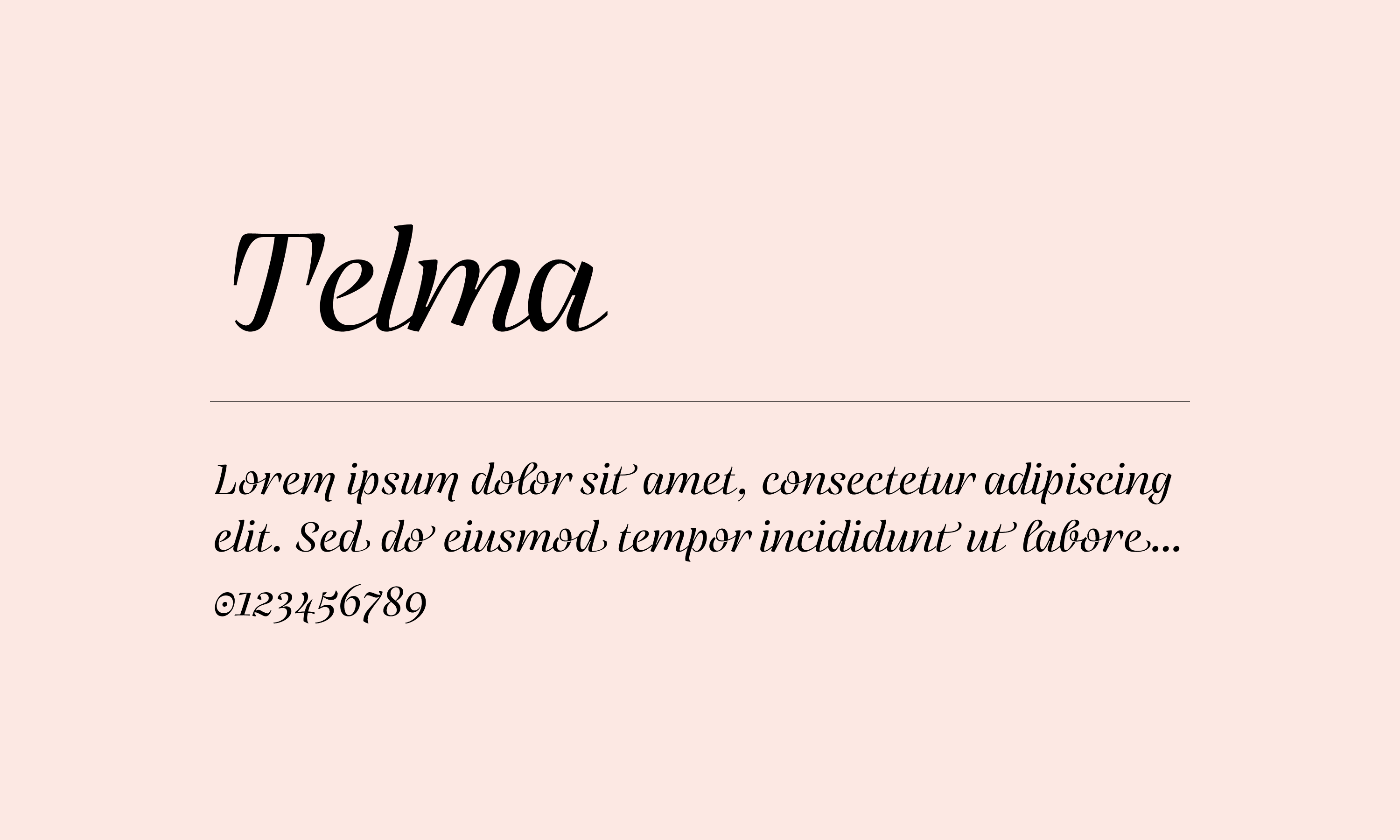
Telma
Telma 是一款非正式手写体字体家族。它的字形具有明显的粗细对比,这种对比赋予了某些字符的古怪结构一种更正式的特点。Telma 字体家族有五种字重,从 Light 到 Black 不等。每当字重增加时,字体的粗线条变得更粗,而细线条的粗细保持不变。该字体还包括多个连字和字形的替代版本;当启用 OpenType 功能中的连字和上下文替代时,这些字形会自动替换进文本中。